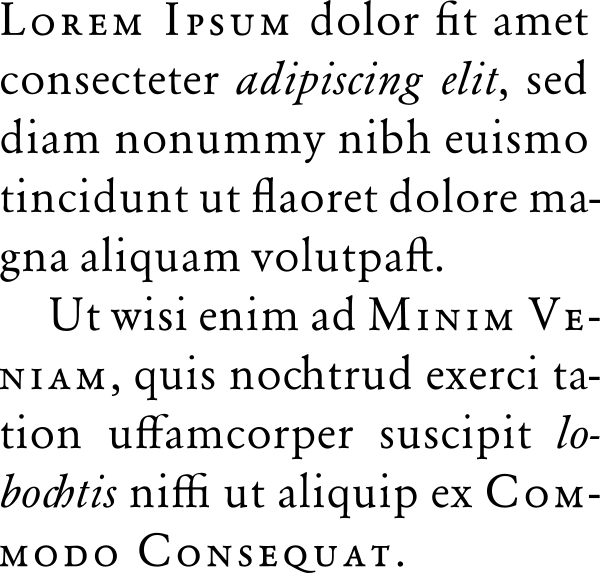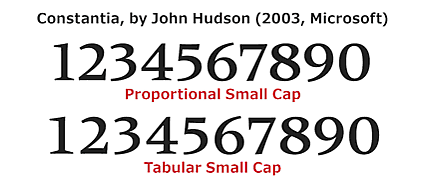
Капитель (шрифт)
Малые заглавные, или капите́ль (англ. small caps; нем. Kapitälchen; от лат. capitellum — головка) — начертание в гарнитуре, в которой строчные знаки выглядят как уменьшенные заглавные. Чтобы подчеркнуть разницу между капителью и строчными буквами, её делают немного выше строчных, а полуапроши капительных знаков увеличивают.
Нередко капитель имитируют, уменьшая заглавные буквы, но этого следует избегать, так как они заметно отличаются по насыщенности, контрасту и ширине.
В настоящей капители толщина штрихов и межсимвольные интервалы совпадают с таковыми у остальных букв. Кроме того, капительные буквы несколько выше строчных и имеют, как правило, чуть расширенные пропорции.
Применение
Капитель применяется в латинском наборе со времён рукописных книг.
Рекомендуется использовать капитель в следующих случаях:
- в аббревиатурах (вместо заглавных букв),
- при наборе римских цифр,
- для выделения имён (в сочетании с заглавными буквами),
- для выделения первого слова, а изредка и всей первой строки новой главы, чтобы «ясно обозначить начало главы» (Я. Чихольд), а также, в случае применения буквицы (инициала), чтобы «смягчить переход от инициала к строчным буквам» (А. Королькова),
- для выделения имён героев при печати драматургических произведений и сценариев; традиционно в отечественной типографике при наборе имён применяется разрядка строчных букв, чего специалисты настоятельно рекомендуют не делать.
Нежелательно набирать капителью длинные (больше двух-трёх слов) фразы и предложения: это ухудшает читаемость текста.
С капителью применяются, как правило, минускульные цифры. Новым явлением в типографике можно назвать капительные цифры. К примеру, они есть в шрифте Constantia (разработчик — Джон Хадсон), входящем в операционную систему Windows.
Капитель в кириллических шрифтах
В современной кириллице большинство строчных букв прямого начертания (за исключением «Аа», «Бб», «Ее», «Іі», «Рр», «Уу», «Фф», «Ѣѣ», «Ћћ» и «Ђђ», не считая букв, созданных на их основе путём добавления надстрочных знаков) практически полностью повторяет рисунок заглавных. Поэтому капитель крайне редко применяется в русской типографике в качестве выделительного начертания (Смерть в романах Терри Пратчетта, изначально говоривший капителью, в русских изданиях, как правило, говорит ЗАГЛАВНЫМИ). Однако капитель может использоваться в качестве способа оформления заголовков и надписей.
HTML и CSS
В CSS малые заглавные определяются конструкцией
font-variant: small-capsлибоfont-feature-settings:"smcp".
Первое — капитель как выделительное начертание (если нет настоящей капители, синтезирует её). Второе — капитель как оформительский приём (повторяет свойство OpenType smcp, и если в шрифте таких символов нет, ничего не делает).
Пример 1 (в CSS заданы несколько шрифтов, в которых есть капитель):
Это — обычные строчные буквы. Обратите внимание на «а», «б», «е», «р», «у», «ф».
Этот текст отобразится искусственной капителью, если шрифт не поддерживает настоящую.
А этот текст отобразится в настоящей капители, если она поддерживается браузером и шрифтом, в противном случае — строчными буквами: This is a small caps case.
Пример 2 (в CSS заданы несколько шрифтов, в которых нет капители):
Это — обычные строчные буквы. Обратите внимание на «а», «б», «е», «р», «у», «ф».
Этот текст отобразится искусственной капителью, если шрифт не поддерживает настоящую.
А этот текст отобразится в настоящей капители, если она поддерживается браузером и шрифтом, в противном случае — строчными буквами: This is a small caps case.
Капитель в фонетике
В Международном фонетическом алфавите используются капительные буквы ʙ, ɢ, ʛ, ʜ, ɪ, ʟ, ɴ, ɶ, ʀ, ʁ[1].
Капитель использовалась в письменности средневекового исландского языка для обозначения геминированной формы согласного, передаваемого с помощью обычной формы буквы[2]. В Уральском фонетическом алфавите капительные буквы передают частично оглушённые согласные[3][4].
Юникод
Капитель считается вариантом начертания и поэтому Юникодом отдельно не покрывается. Однако из-за использования капительного начертания в фонетике в Юникоде есть все капительные буквы стандартной латиницы, кроме X, а также некоторые другие. Они находятся в блоках Расширения МФА, Фонетические расширения и Расширенная латиница — D.